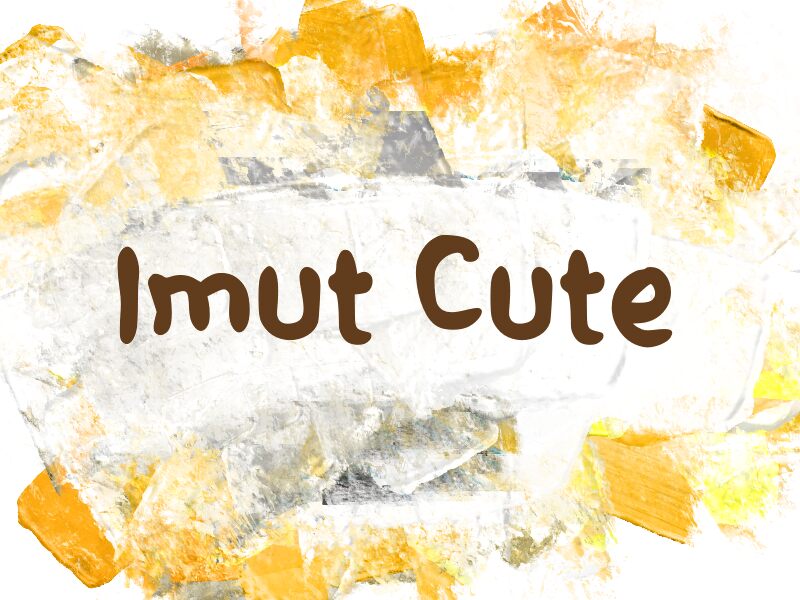
Imute Cute
Imute Cute di Wep è un font display in stile cartoon, gratuito e dal tocco morbido e rimbalzante. Le lettere sembrano disegnate a mano e quasi sciolte, con tratti spessi e arrotondati, curve irregolari e un’oscillazione giocosa che mantiene l’atmosfera leggera invece che ordinata.
È perfetto per branding allegro, packaging per bambini, design di adesivi, menu di bar informali e titoli per i social media, dove un font gratuito può dare il tono da solo. Dato che le forme sono così cicciotte e amichevoli, funziona molto bene anche per brevi titoli, copertine e loghi semplici che devono risultare accessibili al primo sguardo.